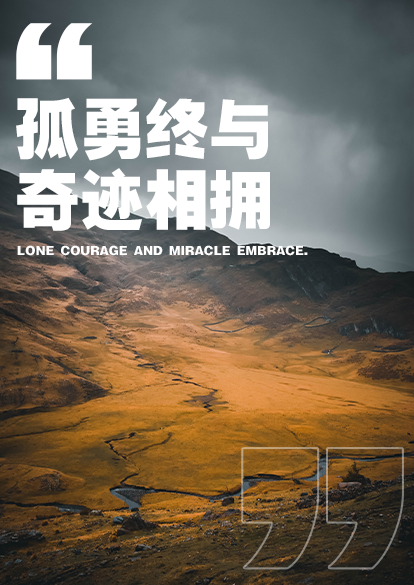
励字超粗黑简繁
Dream-ChaoCuHeiGBT
字体名称:
励字超粗黑简繁
字符集:
GBT
字体语言:
简繁
书体类型:
黑体
字体类型:
普通字体
字体字重:
常规(Regular)
山海皆可平
有力量感的标题黑体字。不是完全的正方形,笔画会有斜度设计,营造出一种动感。横竖笔形粗细视觉相等、笔形方头方尾、黑白均匀,非常醒目,用广泛。